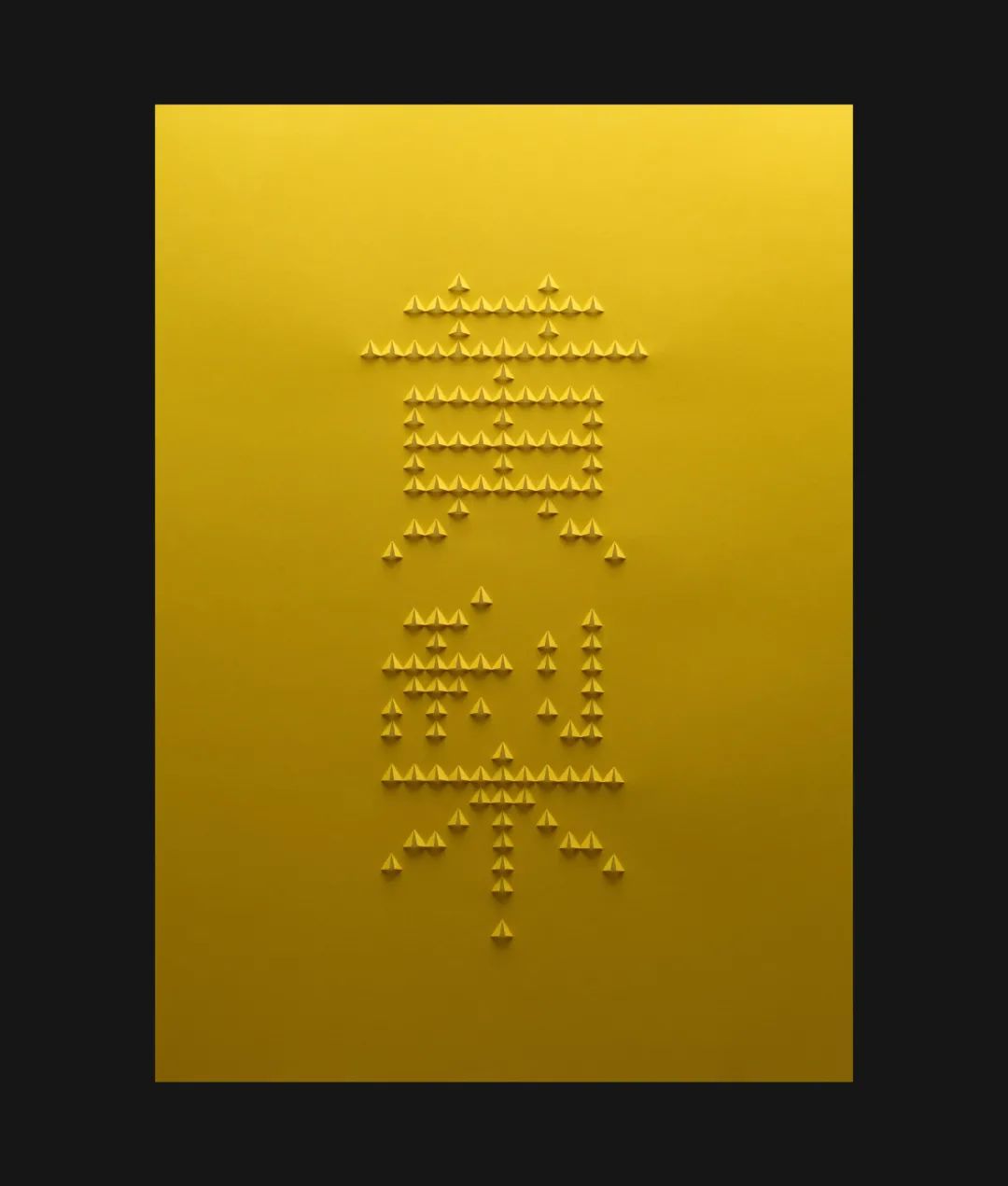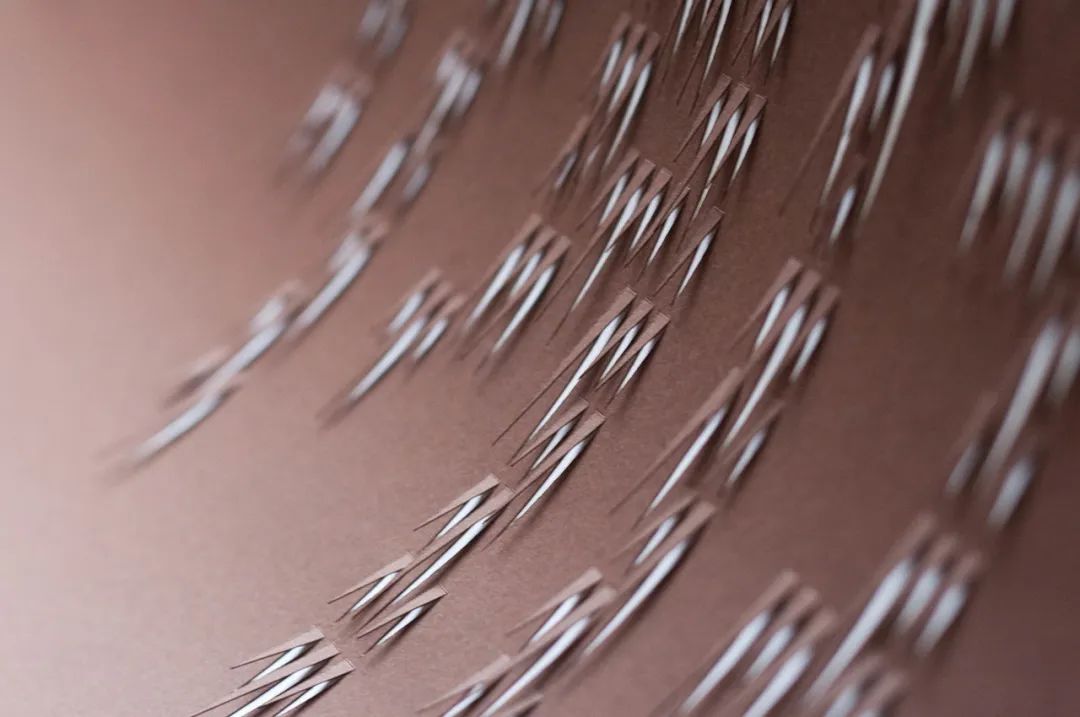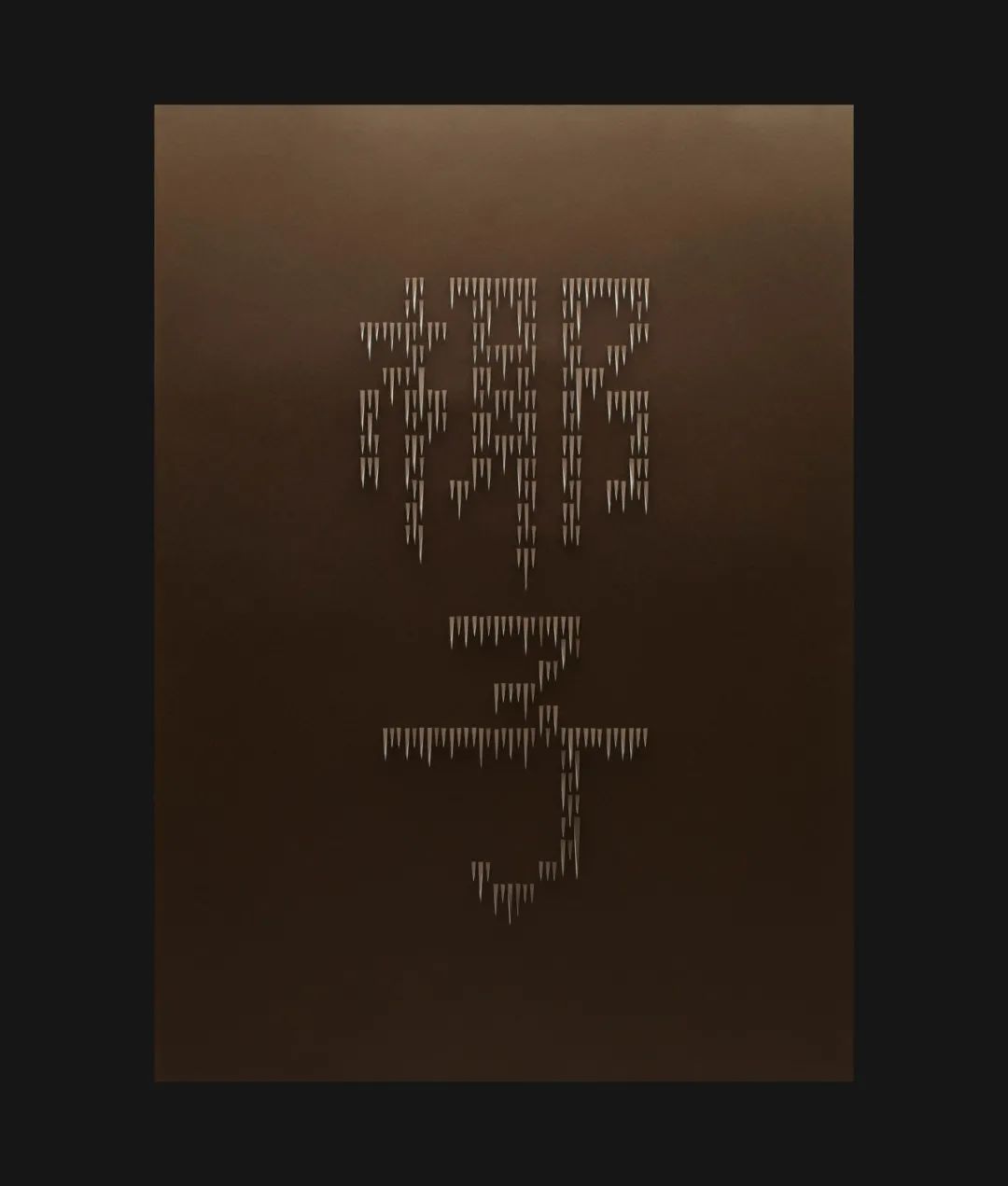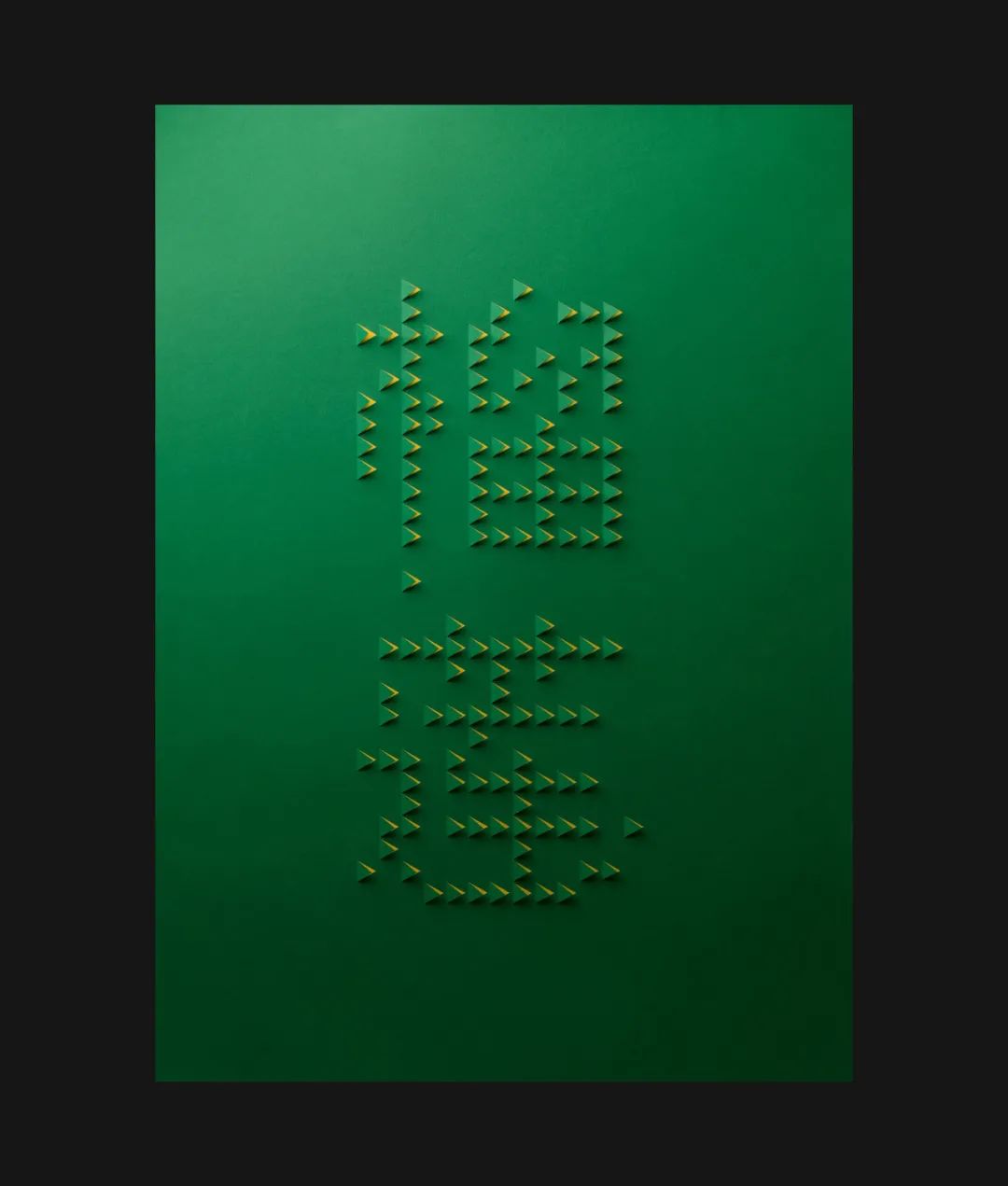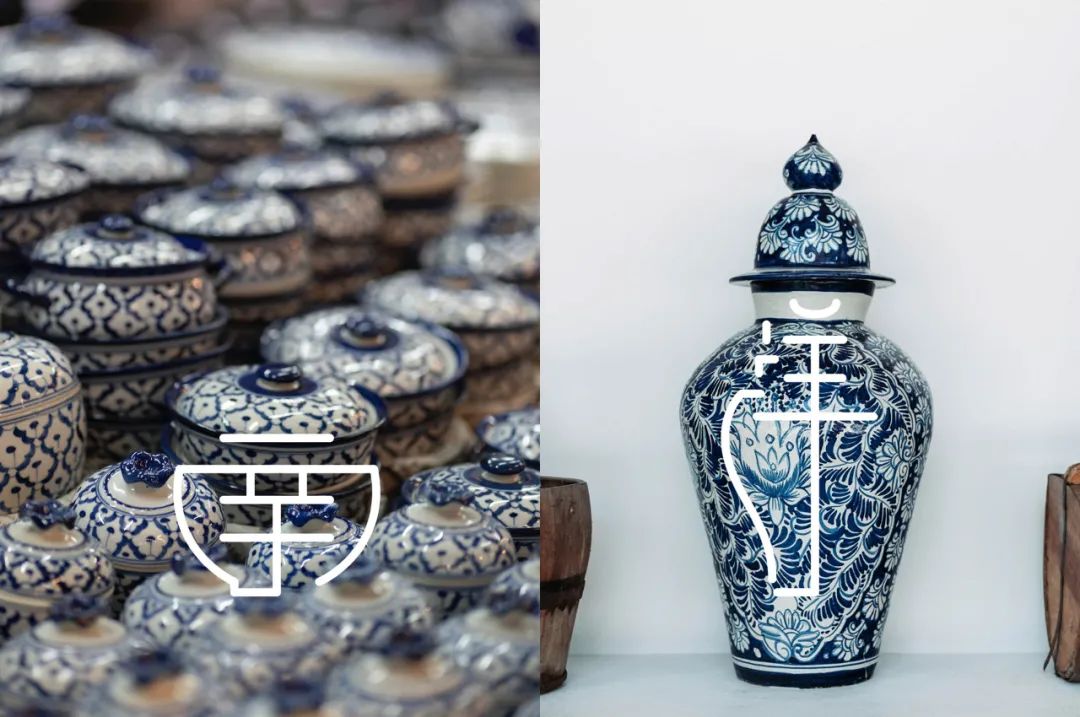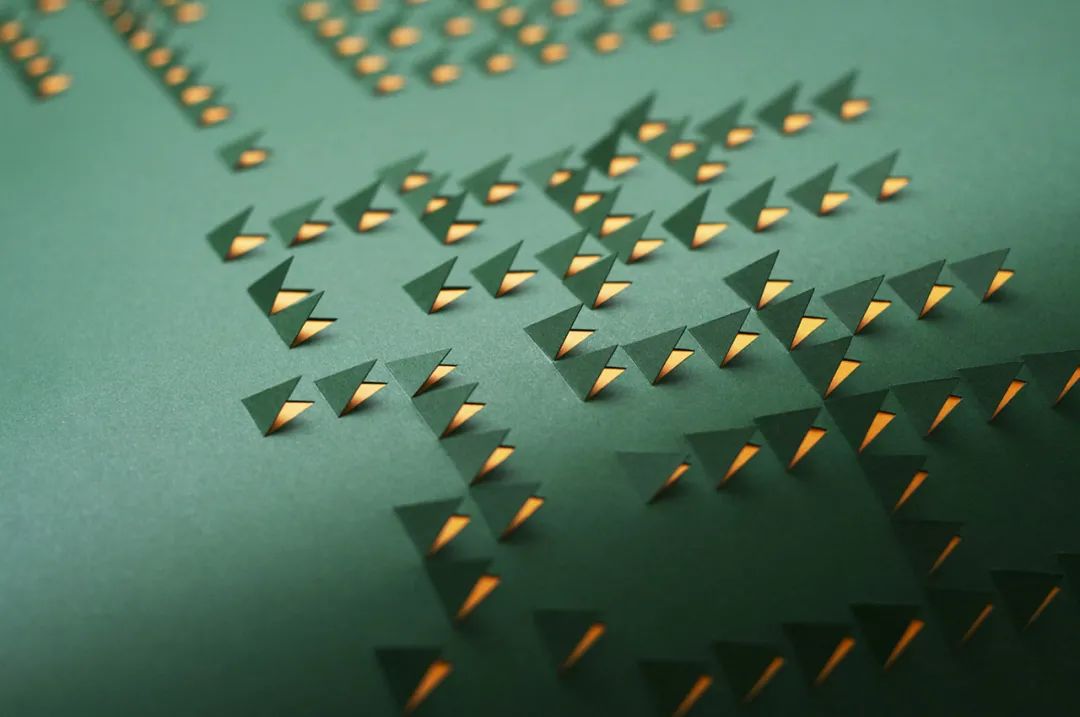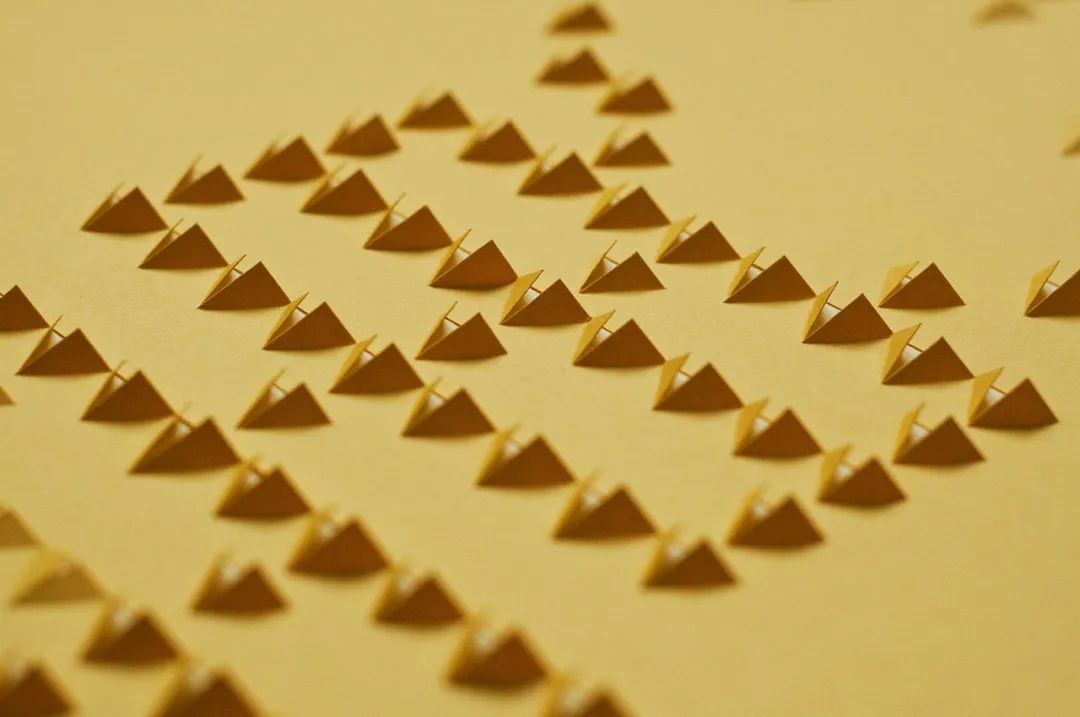
新加坡这家工作室,喜欢玩字体设计
今天,和大家介绍一家来自新加坡的设计工作室。
Roots,是一家独立的品牌和创意设计工作室。凭借对文化、理念和工艺的高度关注,他们为来自各个行业的众多知名品牌、企业和机构,开发服务了意义(并获得认可)的设计故事。
另外有一点,他们特别喜欢玩字体,擅长将字体灵活运用到商业设计项目当中。
今天将通过 Roots 的一系列作品,也认识一下这家设计工作室。
玩 字 / 01
systems14 redux edition
这是 Roots为“ systems14”展览设计的海报。海报以新的深色作为背景色,同时将“东西”二字进行了有趣的创意设计。
玩 字 / 02
榴莲 / 椰子 / 黄梨
Roots 为“ Makanlah Buah-Buahan Tempatan”(让我们来吃本地水果)构思和设计了一系列三个字体海报,该展览通过艺术和设计庆祝马来西亚本地水果。
据介绍,每张海报都是用汉字表示当地水果的名称。这些视觉和纹理处理方法通过在彩色纸上用剪纸技术完全表达出各种几何形状,使之与水果的真实皮肤和果肉相匹配,从而直观地唤起观众对水果的熟悉记忆。
玩 字 / 03
南阳瓷品牌LOGO设计
“南洋瓷器”是Supermama的新瓷器标签。该品牌旨在通过与各种工匠和艺术家的合作,生产出新的原创和现代南洋瓷器设计。我们概念化并设计了标签品牌标识。
南阳的瓷器艺术起源于中国,作为碗,花瓶和小雕像的装饰物具有悠久的传统。为了加强新标签的叙事关联和地理环境,徽标以瓷碗和花瓶的经典形式表示为汉字徽标-南洋(Nanyang)。
玩 字 / 04
滨海艺术中心礼物 | da:ns Festival
“ da:ns Festival ”由滨海艺术中心(Esplanade)举办,是一年一度的庆祝舞蹈和表演艺术的节日。Roots 致力于为电影节构思主视觉设计。
Roots 设计了一个标题文字,使用书法来捕捉表达舞蹈节奏的流畅性。然后,将标头广告与精选的效果图片和文字详细信息组合在一起,以合成最终的主视觉效果。
玩 字 / 05
真理棱镜《众相》
由“滨海艺术节”作为“华谊2020年-中国艺术节”阵容的一部分,《众相》是一种混合媒体参与式体验,使观众踏上了考察和挑战自然的本质旅程。
作为参与表演,观众必须对整个展览中出现的迷宫般的陈述和证据进行讨论,并就实际发生的事情得出自己的结论。对事实和虚构事物,真理和欺骗性质的理解逐渐受到挑战。
为了反映这种微妙的道德歧义,在中文标题的设计上,将“众”中嵌入了一种不平衡的司法尺度,该尺度很容易左右摇摆。这种具有象征意义的装置,就像表演的一部分一样,留给观众发现和辨别。
接下来,和大家看看其服务的几个品牌视觉设计。
品 牌 视 觉 / 01
Super Human
Super Human 是一家新创业公司,专注于使用优质天然成分进行营养优化的膳食补充剂。Roots 为其首款产品 Super Meal 概念化并设计了视觉识别、品牌框架和包装。
Roots 利用通过敲击出来的字“Super Human”,一个正在超过人类的性能极限,这种简单但意义重大的字体并置方式,以直观而优雅的方式表达了品牌精神。
反过来,这种视觉系统构成了灵活的品牌框架的基础,该框架使Super Human可以将其品牌叙述扩展到任何未来的“ Super”产品。
超级餐
Super Human 的首款产品,这是从核心品牌框架扩展而来的子品牌的示例。
品 牌 视 觉 / 02
Pinwheel Jewels
Pinwheel Jewels 是一家位于新加坡的时尚珠宝零售商。我们以崭新的视觉方向对其品牌进行了重新命名,从而赋予了品牌标识真实性。
利用风车中对称的几何形状,在宝石切割中发现多面表面图案之后,就形成了视觉识别。独特的视觉标记直观地传达了品牌所代表的含义。
品 牌 视 觉 / 03
Gracesmiths
Gracesmiths 是一个新的在线零售品牌,带有原创、现代且经过精心设计的同名商标和其他基督教礼品标签。
使用丝带作为形成 Gracesmiths 商标的工具,可以传达品牌的目的和本质,而无需进一步说明。
品 牌 视 觉 / 04
新加坡青年节(SYF)2018大师班
在新加坡教育部的邀请下,Roots为2018年新加坡青年节(SYF)LOGO比赛决赛入围者设计并举办了一系列徽标设计大师班。
视觉识别中的小写字母到大写字母的印刷作品,表达了“青年”的成长,并庆祝节日比赛的创造力。